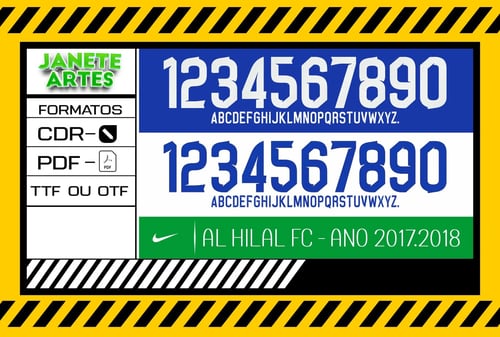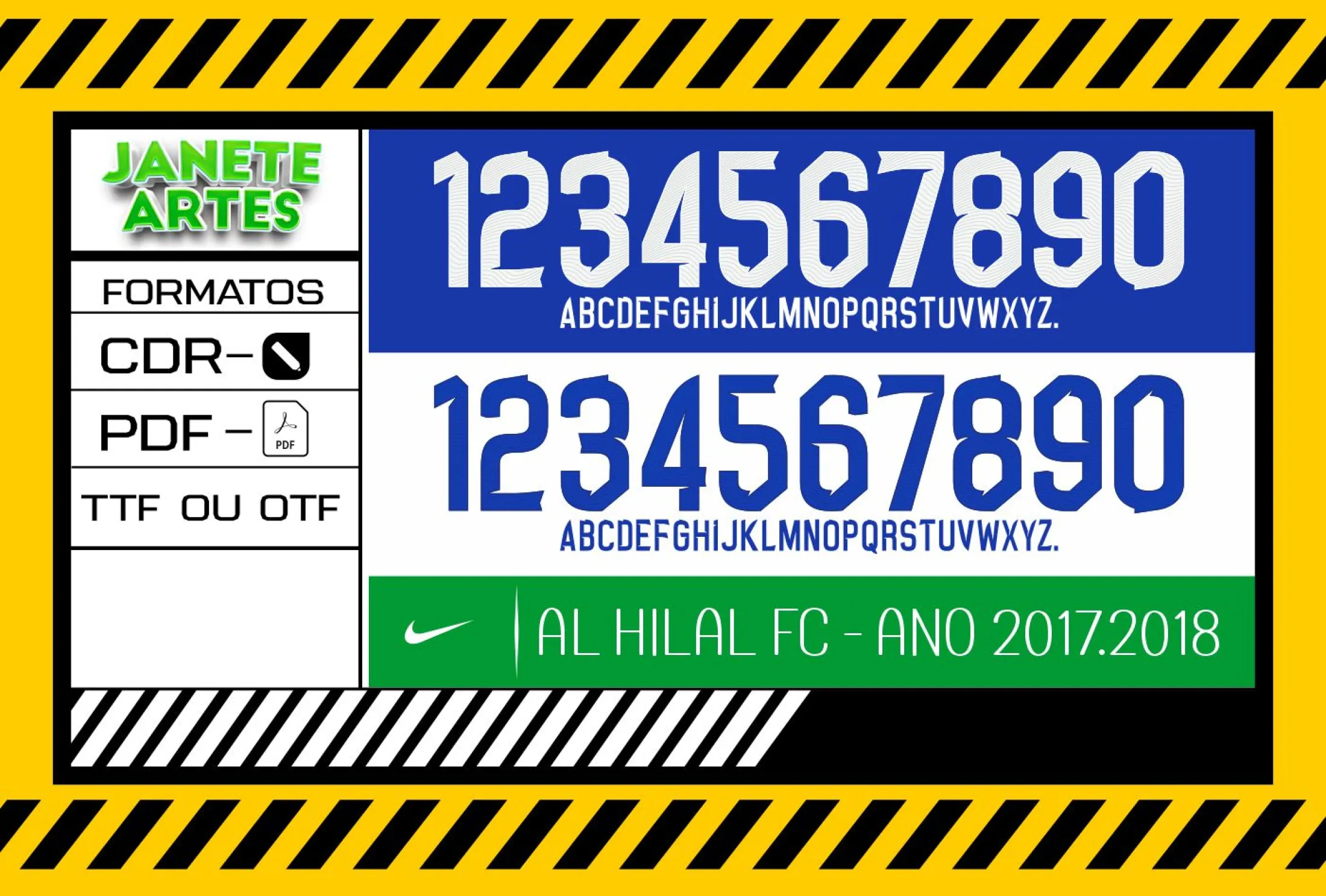
Fonte de Time Tipografia Al Hilal FC 2017 - 2018 Nike
Adquira a Fonte de Time Tipografia Al Hilal FC 2017 - 2018 Nike para criar camisetas personalizadas com estilo único. Perfeita para personalizar camisas de torcida, eventos e times, com alta qualidade e design esportivo marcante.
Uma história de paixão e design para torcedores
Imagine estar em um estádio vibrando com seu time favorito, o Al Hilal FC, durante a temporada 2017 - 2018, com a camisa perfeita, que carrega o estilo e a personalidade do clube e da Nike. A tipografia dessa fonte de time é lendária entre os fãs e agora você pode trazer esse visual exclusivo para suas criações. Seja para eventos, torcida organizada ou presente especial, a emoção de vestir algo personalizado nunca foi tão real. A sensação de ter uma camisa que destaca seu amor pelo futebol, com a mesma fonte que marcou aquela temporada, é única e inesquecível.
• Permite customizar nomes, números e desenhos para criar camisas com identidade própria.
• Ideal para projetos de equipe, eventos esportivos, presentes e coleções exclusivas.
• Combine diferentes cores de camiseta para criar mais opções de uniformes.
• Use a fonte para nomes e números, garantindo a autenticidade do estilo Al Hilal FC.
• Perfeito para grupos de torcida que querem uniformidade e estilo na arquibancada.
• Ótimo presente para fãs de futebol que valorizam design esportivo e originalidade.
• Essa fonte é exclusiva do Al Hilal FC? Sim, inspirada na tipografia usada na temporada 2017 - 2018 pelo clube.